原来最近这种火爆的字,叫逆反差字体
「奇技淫巧」
近年来,一种小众的字体风格再度流行,受到了诸多平面与字体设计师的热烈追捧,似乎一股新兴的设计浪潮正蓄势待发。这种字体风格常被称作——逆反差(reverse contrast)。字体设计师皮特·比亚克(Peter Biľak)曾将逆反差的过程称为「设计脱颖而出的奇特字母造形的奇技淫巧」。经过逆反差处理的字体,能营造出比起普通字体更夸张、更怪诞、更具张力的视觉效果,以逆反差字体为素材的平面设计能表达更富有情绪、更戏剧化的画面。
Ture Festival 视觉识别系统 by mateusyuzo
边集 Editor 视觉识别系统 by A Black Cover Design
屡屡获奖的 Ribaasu 字体 by Tien-Min Liao
「逆反差」一词是从英文「reverse contrast」翻译而来,有时也被称为「reverse stress」或者「reverse stroke」。一般来说,用右手以平尖笔书写西文书法时,笔头会与书写方向保持一个比较固定的锐角。由于各个字母造型本身笔画的长度方向不同,书写时字形会发生较强的粗细变化,足以成为拉丁字母具有代表性的一个特征。现代西文字体设计中称之为「contrast」,以描述字体中粗笔画和细笔画之间的对比关系。若形容一款字体具有高对比 high contrast,那么说明它笔画粗的很粗、细的很细,两者差得很多,比如 Didone 风格的字体;反之,低对比 low contrast 则指字体笔画粗细对比小粗度相当,许多无衬线体就是如此。
二十世纪中,荷兰著名书法家和设计师格里特·诺泽尔(Gerrit Noordzij)发明了一套书写理论以解释西文书写中笔势的变化,并倡导以书写走向作为字体设计的基础。他认为如果没有这支想象中游走纸上的笔,光靠字体轮廓设计是行不通的。依平尖笔书写习惯,笔画在方向上越倾向笔头与书写方向的角度,视觉上就越细,从粗到细往往可以看到逐步变化的过程。点尖笔则不同,通过在纵向运笔时给笔尖施加额外的压力,使墨水能够从笔头大量溢出,笔画能迅速变粗,从而实现更加突出的粗细对比效果。它们对应的即是诺泽尔称为「translation」(平移)和「expansion」(扩张)的两套笔画逻辑。
Translation & Expansion. The Stroke Theory of Writing by Gerrit Noordzij
诺泽尔构建的理论其实反映了一种更普遍的字母造型认知,即拉丁字母的横向笔画往往比竖向笔画来得更细,向上行的笔画比向下行笔画更细,总体给人「横细竖粗」的视觉印象。反过来,若一个字体是「横粗竖细」,那么它就把常规的粗细对比反过来了——故其名曰「reverse contrast」,也就是颠倒过来的粗细对比关系。这种处理与对自文艺复兴以来、以罗马正体和哥特体为代表的拉丁字母审美相距甚远,往往能够在一瞬间就营造出一种怪诞夸张的效果,吸引人目光。至于说为什么中文不直接叫「反对比」,而是用「逆反差」这个听起来更酷的名字,很有可能是纽约字体设计师廖恬敏引领的一股风潮,并没能发现在她如此形容自己的 Ribaasu 字体前有过类似的说法。
但笔画粗细的不同仅仅只描述一个维度,笔画粗细依照什么规律变化依然需要解释。以字母 O 为例,可以在笔画最细处相连做一根轴线表示粗细变化的方向。平尖笔由于存在笔头角度的问题,所以粗细变化的轴线不可能是完全垂直的。以平尖笔书写的西文和早期铅字字体如 Jenson、Garamond、Centaur 等都具有斜向轴线,这也是更具书写感的人文主义风格的体现。点尖笔的使用意味着不需要考虑平尖笔笔头与书写方向角度的问题,可以做到完全垂直的粗细变化轴线,同时实现更强的粗细对比。Baskerville 或 Didone 都倾向于几乎垂直的轴线。因此,我们可以说常规的拉丁字母造型是斜向(diagonal stress)或竖向变粗(vertical stress)的,反过来,逆反差字体则是横向变粗(horizontal stress)。
在美国字体设计师大卫·乔纳森·罗斯(David Jonathan Ross)看来,仅仅笼统地用「逆反差」来描述这类字体还不够,应该更加细致地理解并区分「Reverse Contrast」与「Reverse Stress」这两个概念。根据轴线倾斜的不同角度,可以得到一个变化区间,垂直至左倾 45 度的轴线代表了拉丁字母常规形态字体,称作「Normal Stress」。那么,「Reverse Stress」的粗细变化轴线就应垂直于「Normal Stress」的轴线,这样我们又得到了一个水平至上扬45度的轴线变化区间。
传统拉丁字母造型中的 O,来自 DJR 的演讲 Backasswards
理解 Contrast 就简单了。不考虑粗细变化轴线的角度,把完全的横(水平)细竖(垂直)粗定义为「Normal Contrast」,还是如上图以字母 O 为例,水平笔画的粗度几乎保持不变,竖笔可以细到只比稍微粗一点——粗细对比小;也可以粗到像收缩的猫瞳孔一样——粗细对比大。「Reverse Contrast」则指的是原本在竖直方向的粗细变化横过来了,竖笔粗细保持不变,水平方向的粗度发生变化——横(水平)粗竖(垂直)细。
不过以上皆是从字体设计师从理解设计角度做的分析,在更笼统模糊的口头说法上,「reverse contrast」、「reverse stress」或「reverse stroke」都多少可以交替使用来描述这一类字体风格,中文也索性就称其为「逆反差」了。逆反差字体最重要的特征其实是,它重构了传统拉丁字母造型视觉比例,打破了拉丁字母纵向粗重的视觉印象,从而产生了一种异常奇特的观感。纵向笔画影响阅读节奏(rhythm),进行逆反差处理横向笔画加粗后会导致截然不同的阅读体验。
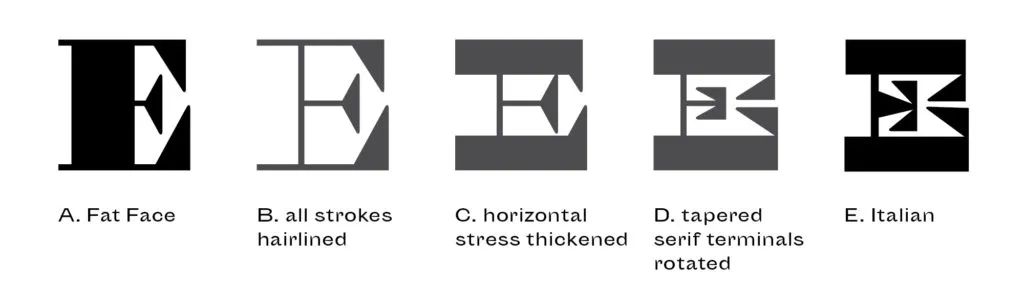
诺泽尔的理论虽然可以解释诞生于十九世纪初、以强烈粗细对比风格的字体为原本进行反转的典型「逆反差」字体——有如上图所示,Caslon Italian 在笔画粗细上几乎能完美地对应流行于十九世纪初欧洲的 Fat Face,大卫·西尔兹(David Shields)更是仔细地还原了 Italian 的可能产生过程;但却无法解释如 French Clarendon 这样的仅在字母上下部分加粗的逆反差字体。所以罗斯提出,这一整类风格与其叫逆反差,不如干脆称作横向加粗(horizontally stressed)字体。当然,命名这种事往往并不会由设计师或理论家钦定,人民群众喜闻乐见显然更加重要。
对比两种逆反差字体的实现方式,来自 DJR 的演讲 Backasswards
「排印怪物」
与今天多少受到设计师追捧的境遇不同,逆反差风格的字体在诞生之初其实饱受争议与批评。近年来,字体设计师和印刷史研究者们对逆反差字体的前世今生抱有极大的热情,像弗吉尼亚联邦大学的大卫·西尔兹教授就追溯了逆反差字体 Caslon Italian 的起源和发展,米兰理工大学的詹姆斯·克拉夫教授(James Clough)则对意大利的逆反差风格木活字做了不少研究。前文提过的皮特·比亚克和大卫·乔纳森·罗斯两位,还有尼克·谢尔曼(Nick Sherman)站在设计师的角度对逆反差字体的视觉风格进行了收集整理。本文从这几人的研究和观察中受益良多。
据西尔兹的研究,逆反差字体最早应可追溯到 19 世纪初,一本 1821 年 Caslon & Catherwood 的字体样册里的 Caslon Italian。最早的 Caslon Italian 都是铸造而成金属活字,仅包含大写字母和数字,并没有小写字母,其设计铸造意图明显是用于商业广告海报张贴。这类字体风格 19 世纪工业革命中期的金属活字行业的一个新奇且激进的创新,就算在今天看来也毫不过时。
Henry Caslon Italian 字体样张,1821 年,Letterform Archive,,来自 DJR 的演讲 Backasswards
保存于 St. Brides Library 中的 Caslon Italian 字冲,Eye Magazine,,来自 DJR 的演讲 Backasswards
橘生淮南的字体
1874 年 Fann Street Foundry 的一本字体样张,其中更粗重的即是 Clarendon
French Antique 字体,来自 DJR 的演讲 Backasswards
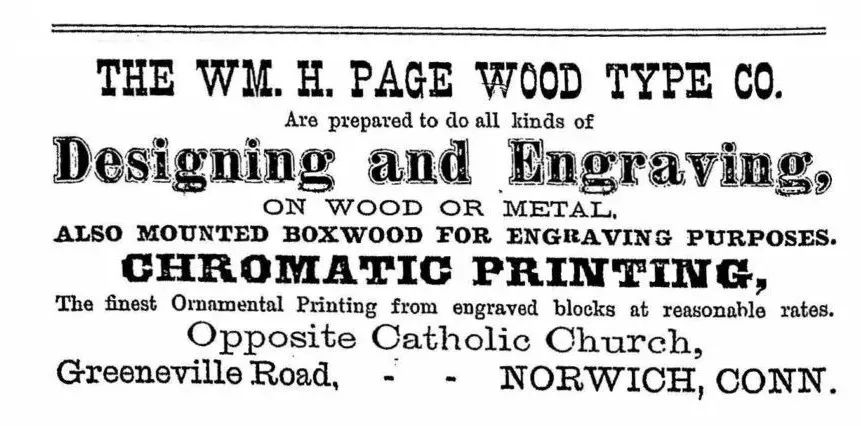
French Clarendon wood type, Hamilton Wood Type Museum
French Clarendon 风格的字体常与「狂野西部」的想象联系在一起,出现在美国西部片中的场景中,以及通缉令、警告牌等道具上,在上个世纪五六十年代的电影行业中颇受欢迎,它也因而成为了逆反差字体风格中一个相当有特色的分支。French Clarendon 被用作西部影片中的「通缉令」并非空穴来风,这种逆反差风格的字体原来就是为告示、张贴和商业海报量身定做的,比如这张十九世纪三十年代伦敦的失马悬赏中,「REWARD」这几个字母已经初具后来的美国西部风的雏形了。
John Soulby collection, University of Reading, via Rafael Dietzsch, Jennifer Kennard
标准的逆反差风格「通缉令」,在美国西部片中非常常见
Gothic Tuscan Italian,Wells & Webb,1854,American Wood Type, as in DJR's Backasswards, Courtesy of David Shields
Italic Italian by Conner & Sons,1855,American Type Founders, as in DJR's Backasswards, Courtesy of David Shields
Tuscan Egyptian,1870,American Wood Type, as in DJR's Backasswards, Courtesy of David Shields
十九世纪末流行于美国的彩色木活字,Rob Roy Kelly 编 American Wood Type 1828 - 1900
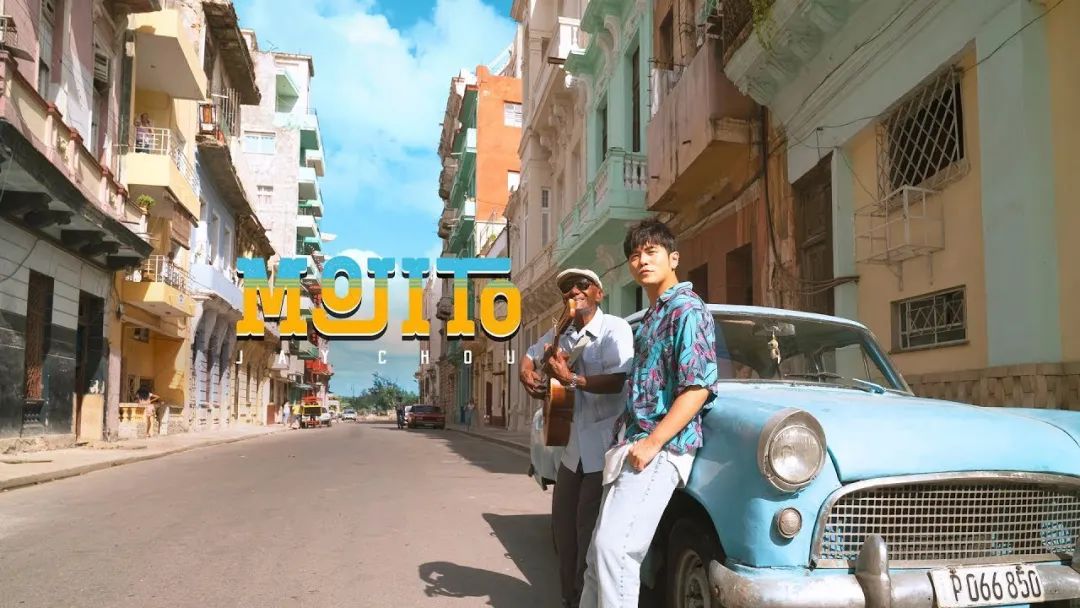
风靡一时的 Playbill 字体,由Robert Harling 复刻
弗鲁提格设计的 Westside,1989,Linotype
风格特点
一般认为,Italian 风格的逆反差与同时期粗细对比强烈的 Didone 类字体具有形态上的关联。皮特·比亚克于 2012 年利用 metafont 技术制作了字体 Karloff。其字体的概念就是将 Didone 和 Italian 作为美与丑的两个极值,通过数值控制生成了一个概念性的字体家族——即美、丑、中性的合集。Karloff 是一款非常实验性的字体,它的市场营销概念也很独具一格。
皮特·比拉克设计的 Kraloff,Typotheque
计算机时代的逆反差
逆反差风格的字体被除了被运用于海报、印刷品、餐厅、店铺招牌等待之外,在游戏中也能发现它的身影。早期计算机时代的游戏制作者们对于塑造新世界的热情却没有被技术所限制。在当时技术条件限制下,制作字体往往只能在总量两位数的像素网格进行,以至于文本内容和标题很难得到明确的区分。而通过加粗横向笔画而得到的逆反差风格,则可以在资源极少的情况下很好地达成这个目的。
Koresh的重量分布
Koresh的字体样张
Caslon Italian的字体样张,Commercial Type
逆反差字体会成为趋势吗?
Future Fonts 上的几款逆反差字体
澳大利亚在线艺术刊物 West Space Journal 的逆反差风格刊头
Sharp Type 推出的 Beatrice Family
苹果推出的新字体 SF Pro Variable
逆反差字体在诞生 200 年后的今天,已经不再像诞生之初那样,独处字体世界的偏僻角落遭人诟病。罗斯在演讲中提到,如果依据诺尔泽笔画理论,仅把粗细变化反转过来,就可以在原来的字体魔方上构造出另一个平行宇宙。随着审美观点的变迁,最初从书写逻辑中诞生的逆反差字体们是否仍然能够满足当下的需求?逐渐远离了书写工具后的现代人,又该如何想象新的逆反差风格?另一方面,这种起源英格兰的怪诞字体风格在我们更熟悉的文字中又是如何表现的?中文和日文逆反差字体的过去和未来又是什么样?且听下回分解。